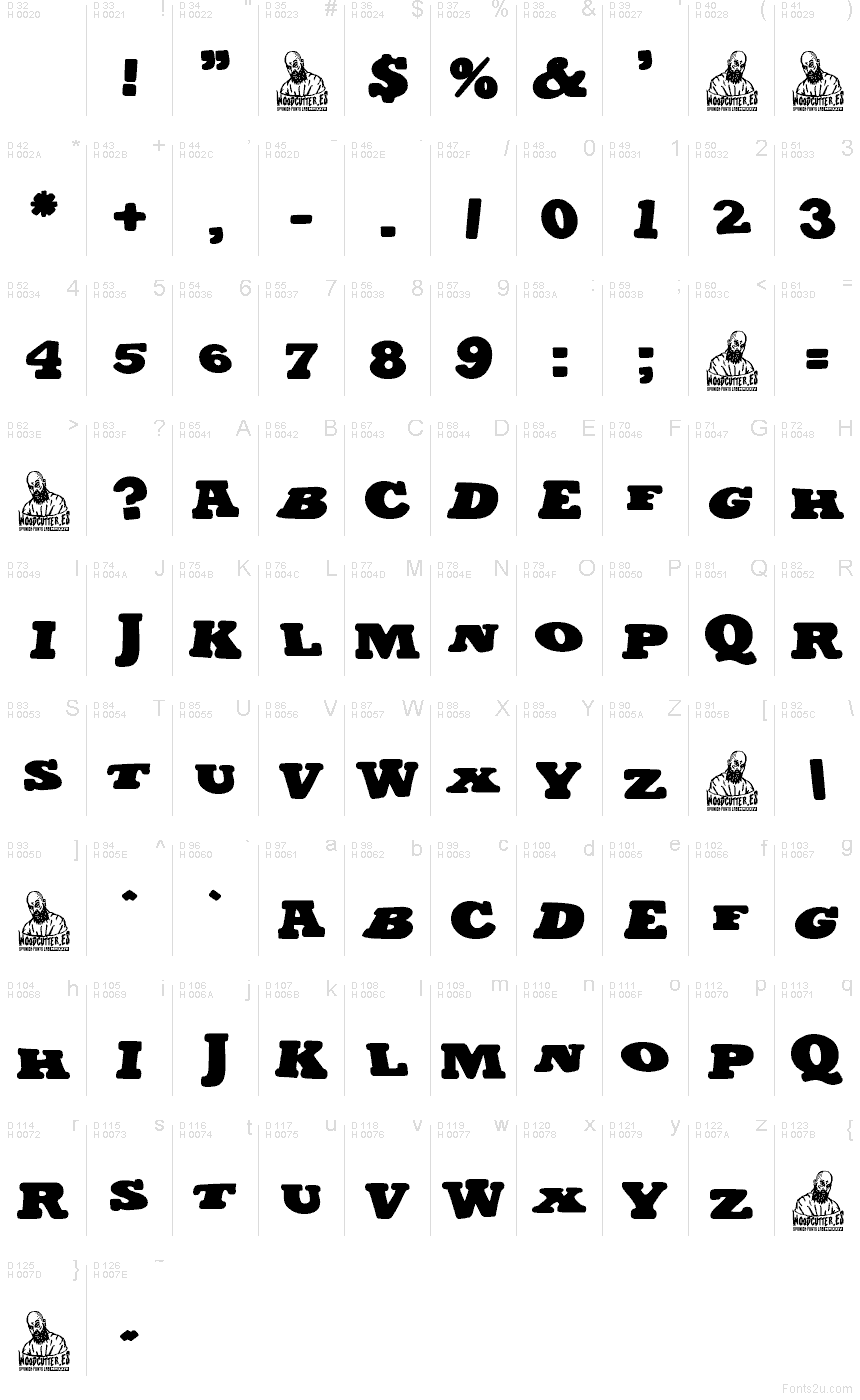
The Chaosland
Písmo Chaosland od Woodcutter Manero je bezplatný komiksový display font so zaoblenými, blokovými tvarmi a mierne nepravidelnými okrajmi, ktoré mu dodávajú ručne vyrezávaný, plagátový nádych. Široké tvary a kompaktný rytmus zabezpečujú, že písmená pôsobia živým dojmom bez toho, aby boli neprehľadné, a mäkké rohy zas chránia dizajn pred prílišnou strnulosťou.
Chaosland funguje výborne v komiksových titulkoch, plagátoch na podujatia, hravých logách, pri tvorbe nálepiek, na detských obaloch či vo výraznej grafike pre sociálne siete, kde vďaka svojim mohutným tvarom skvele vynikne aj v krátkych textoch. Tento bezplatný font sa hodí aj pre ziny, nápisy a merchandising, ak hľadáte písmo, ktoré je hlasné, neformálne a trocha nespútané.